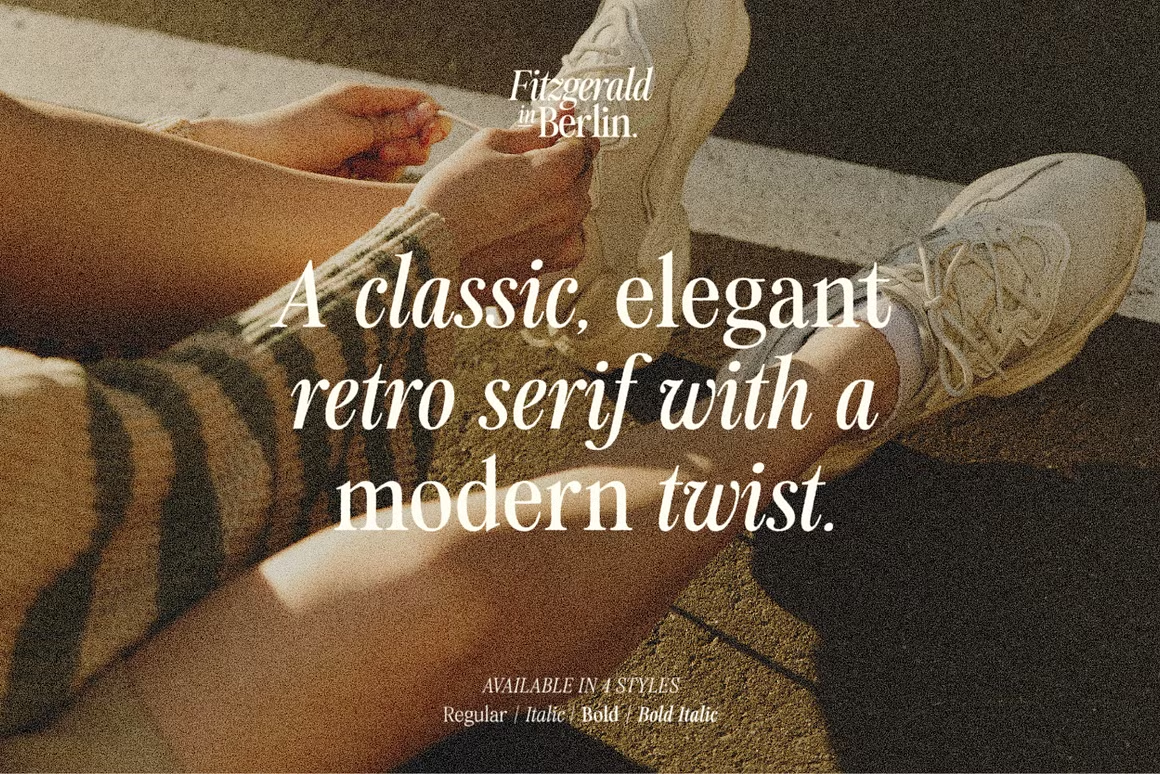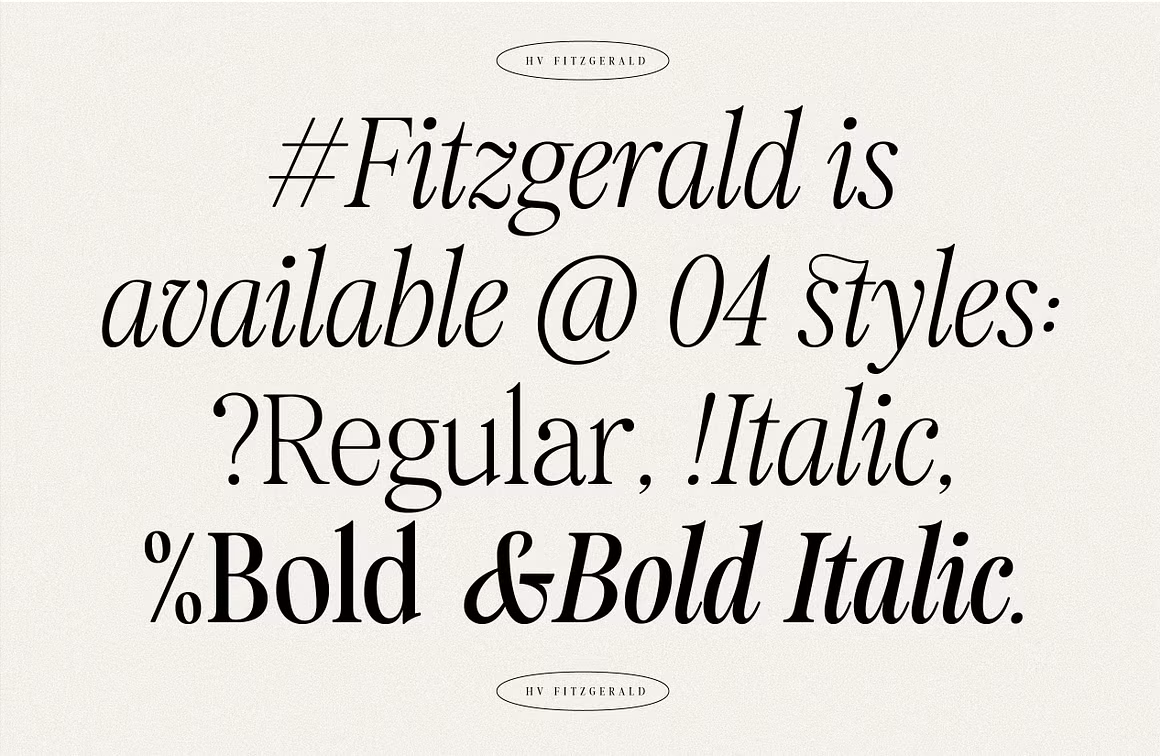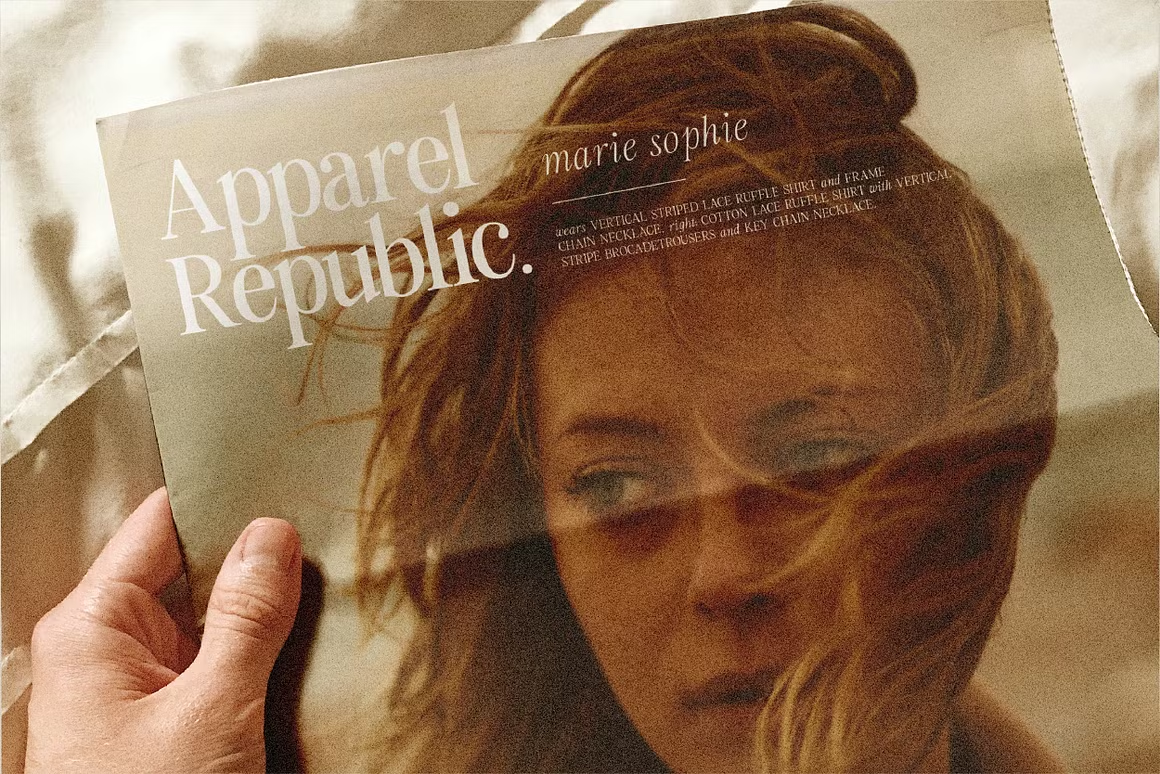
Fitzgerald Font
Description de Fitzgerald Font
Fitzgerald est une police serif épurée et élégante qui a une touche rétro tout en conservant une esthétique moderne. La police est très simple et idéale à utiliser à des fins très diverses, allant de l’affichage des titres à la copie de texte. Créé par Harmonais Visual et inspiré par la tendance nostalgique, Fitzgerald incarne les caractéristiques de la typographie du début des années 1900 avec les principes du design contemporain. Ce mélange est parfait pour créer des designs aux accents rétro tout en conservant un look épuré et élégant.
Caractéristiques de la police Fitzgerald
Fitzgerald est une police à empattement rétro qui a la capacité de créer un look intemporel tout en étant adaptée aux designs contemporains. De plus, certaines des caractéristiques de Fitzgerald incluent le fait qu’il a des empattements en gras et, plus encore, ils rendent le texte plus lisible et lui donnent une touche classique. De plus, le design de la police s’inspire du style rétro qui redevient populaire, combinant le style vintage avec le style moderne pour créer une police épurée et belle. Cela permet à Fitzgerald d’être à la mode et d’être d’actualité, même dans la génération actuelle.
Usage
En raison de sa grande lisibilité, il convient à l’affichage de textes tels que les titres et les affiches, ainsi qu’au corps du texte dans la conception éditoriale, notamment les magazines, les journaux et les livres. De plus, l’élégance de Fitzgerald est idéale pour la publicité, y compris les logos et les emballages, où elle peut apporter une touche de classe et être facilement visible sur les étagères. Qu’il s’agisse de recréer des designs anciens ou d’incorporer une touche vintage dans des designs modernes, le look intemporel et moderne de Fitzgerald est parfait pour les designers.